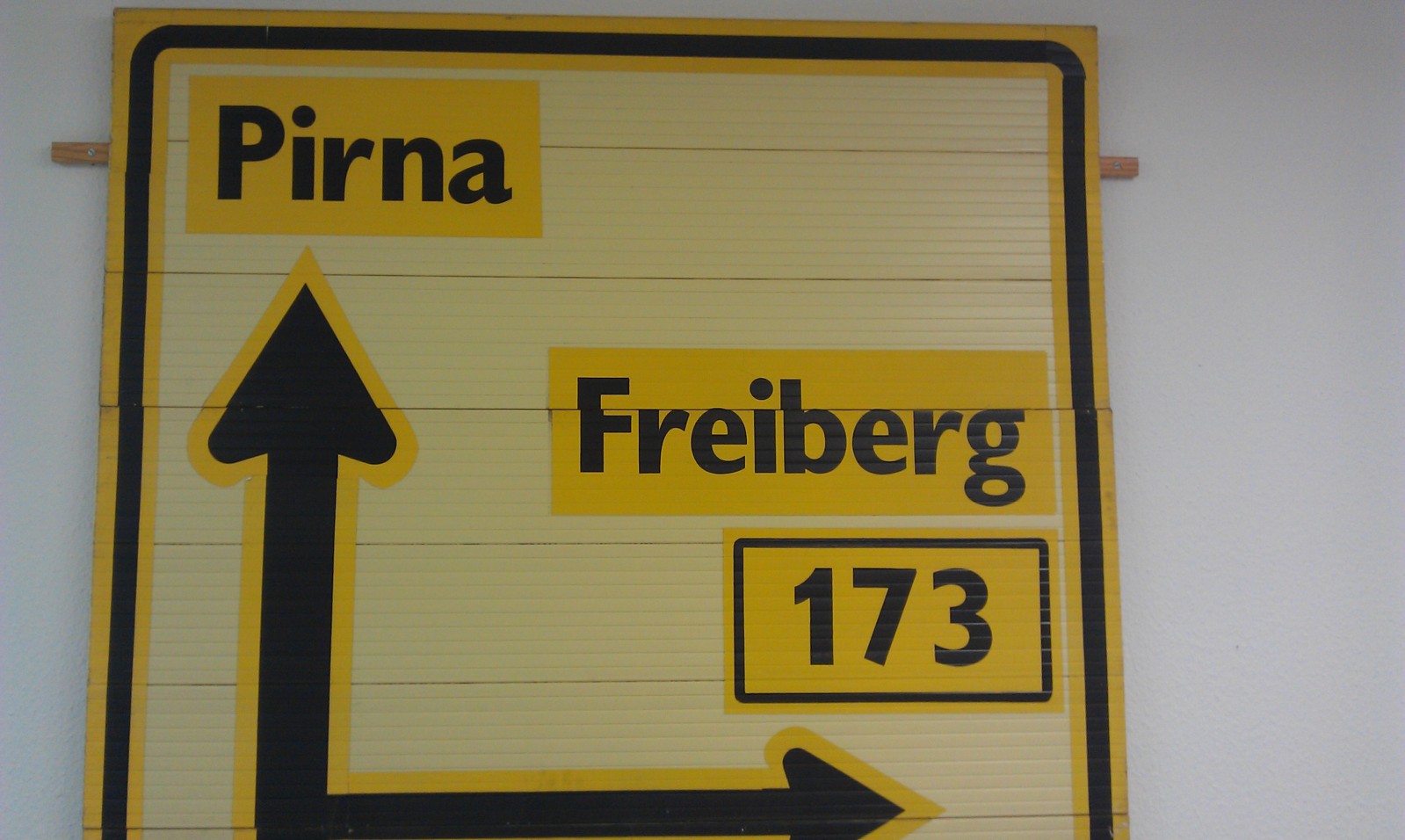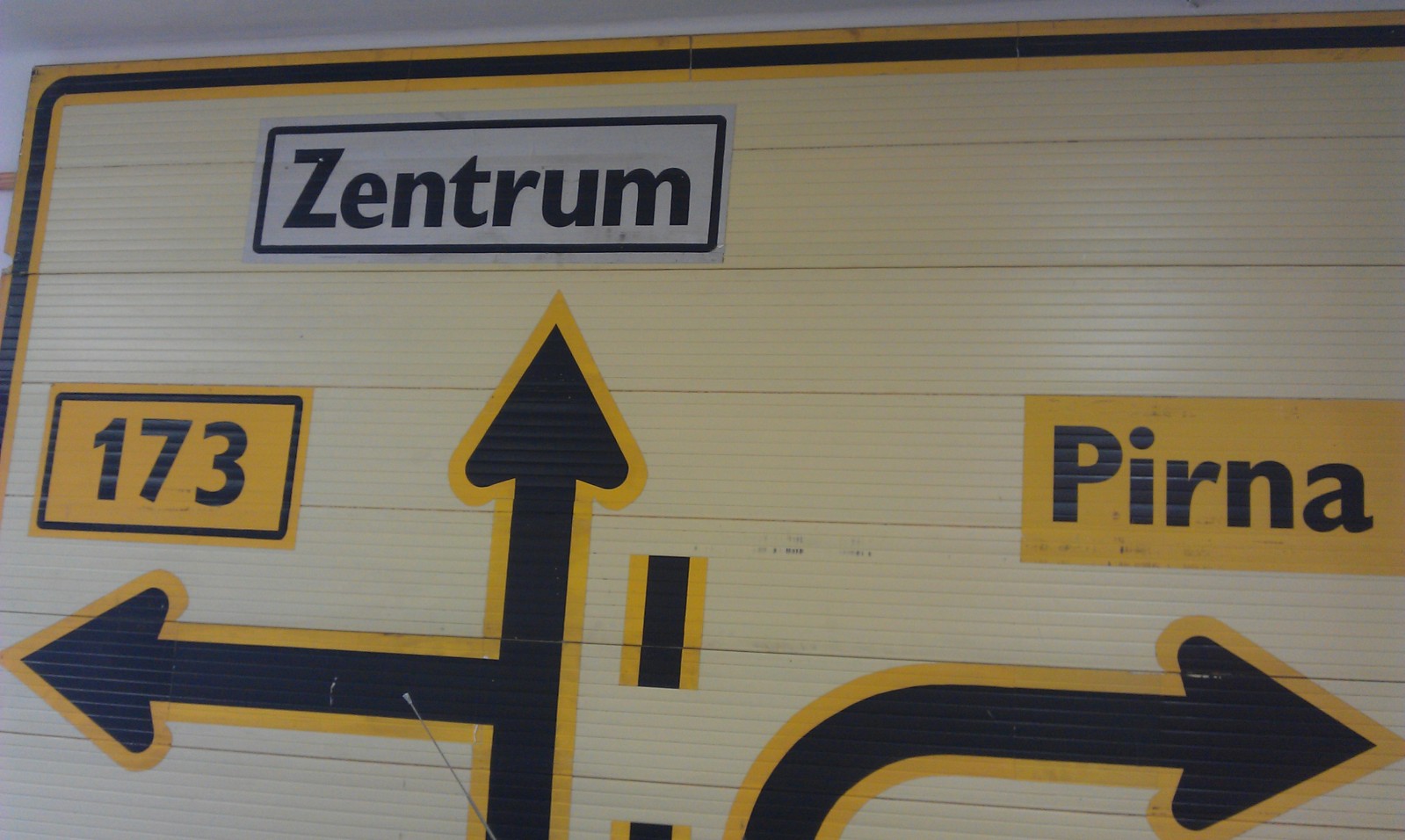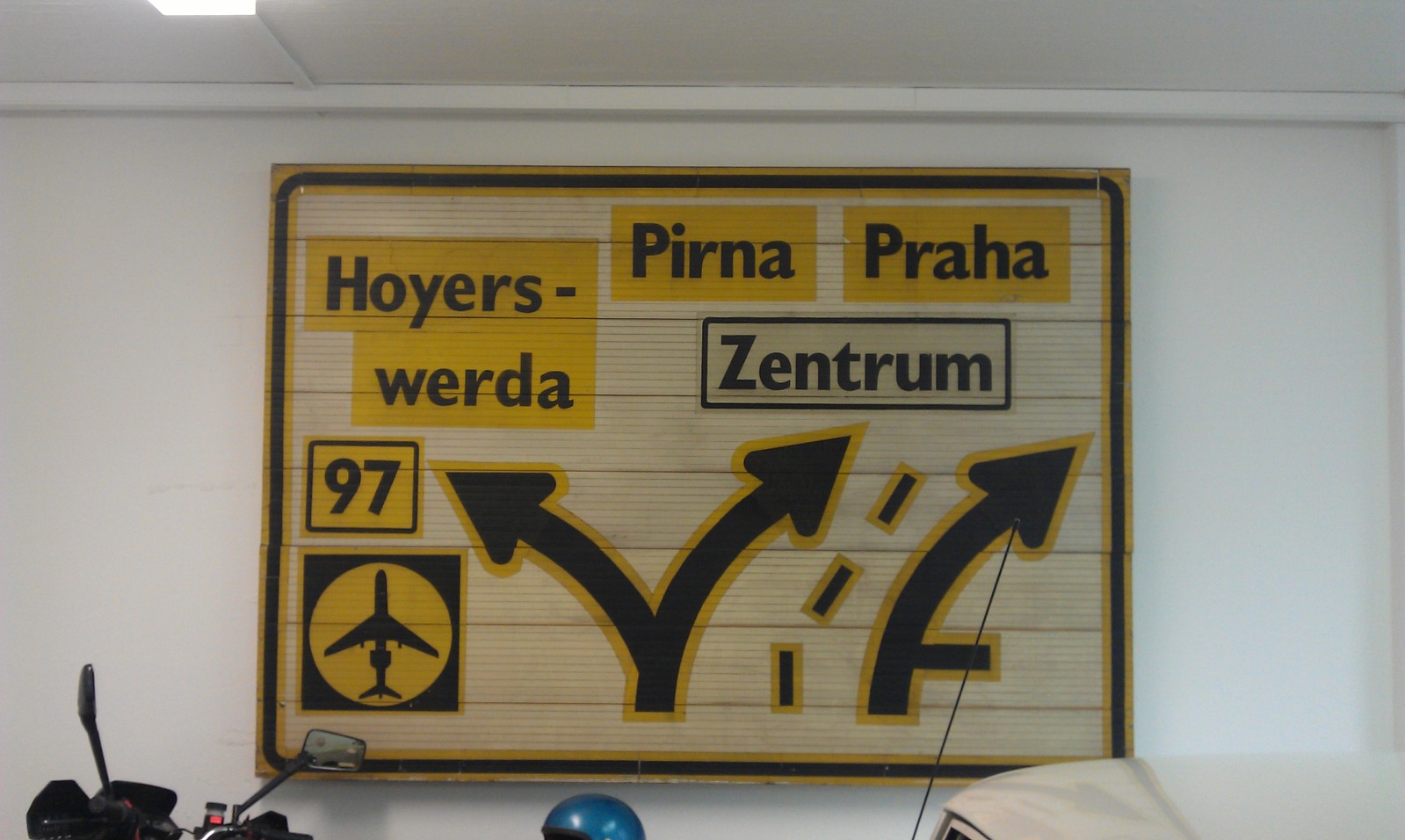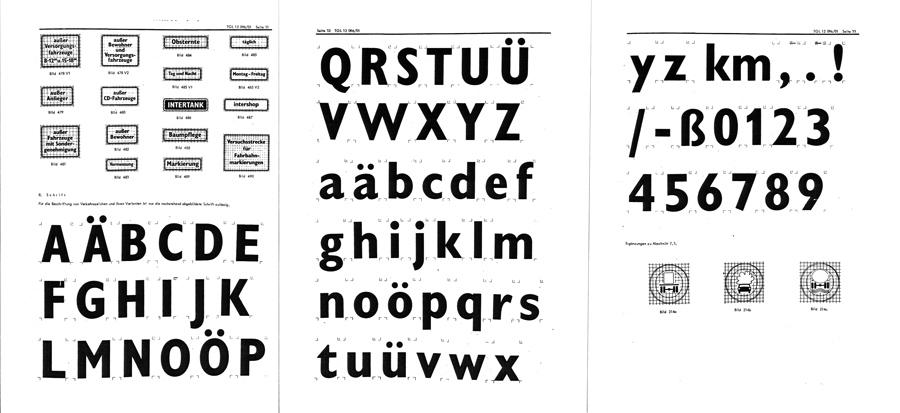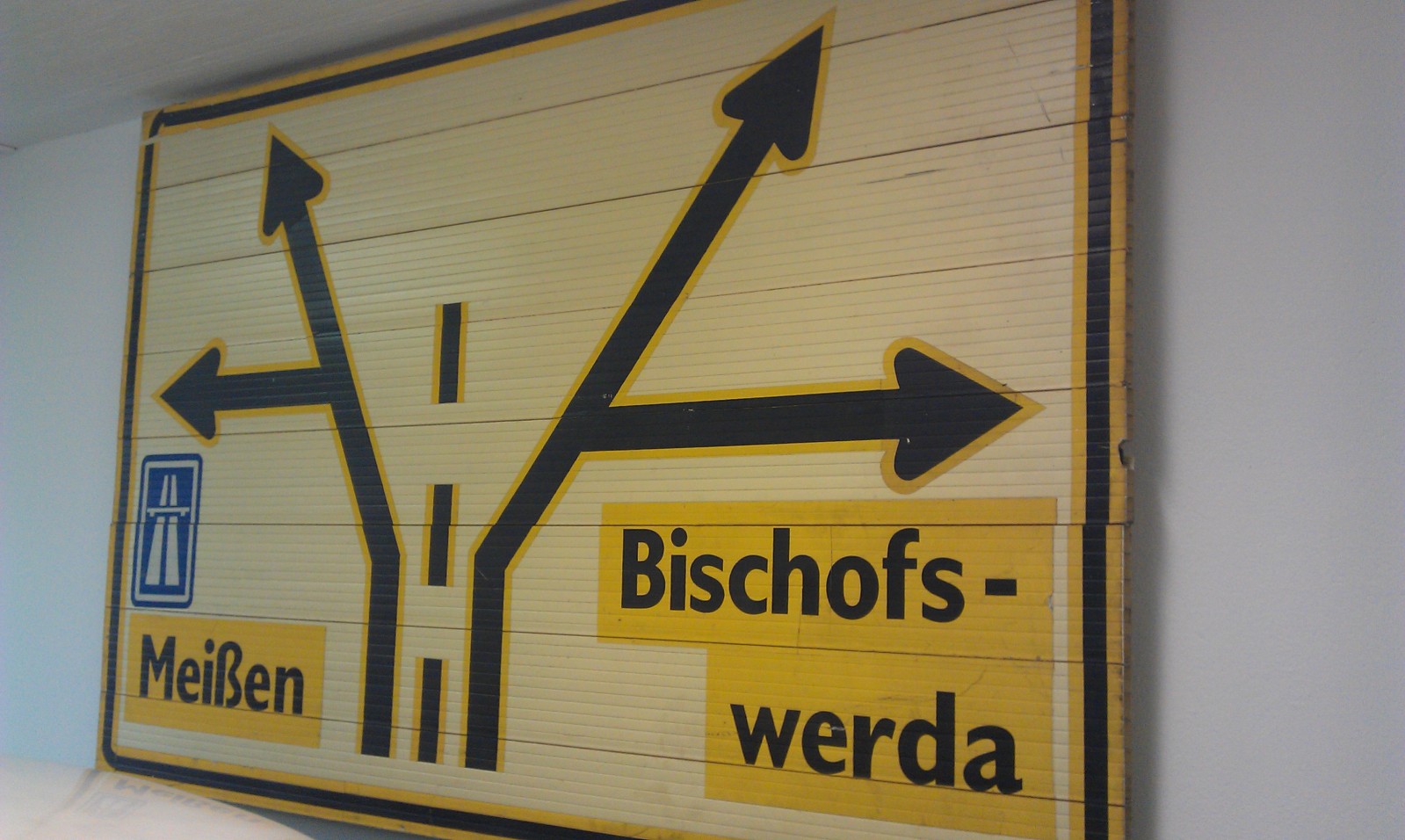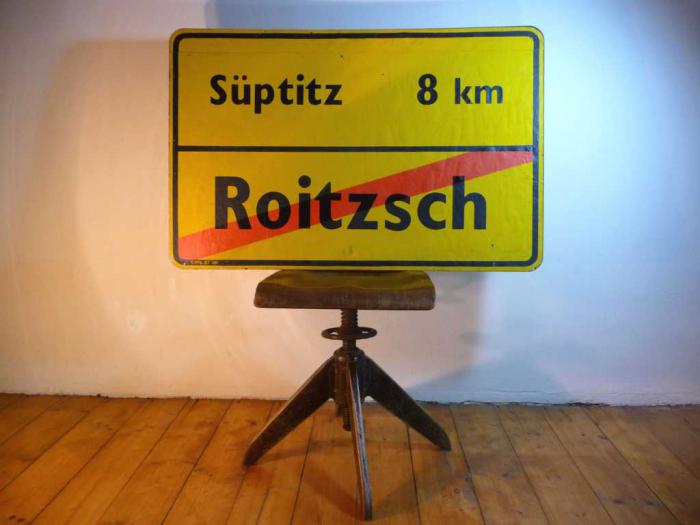
Straßenschilder aus der DDR
Aber die hängen doch nicht an irgendwelchen Wänden, oder? Das sind alte STRAẞEN-Schilder, die gehören an eine Straße und haben den ganz bestimmten Zweck eine Straße zu beschildern ... :mrgreen:
interessant fand ich ja, wie die teile zusammengebaut sind. die bestehen aus plastikschienen – von nah sieht das ziemlich billig aus.
Das Zeug wird bei Frost so spröde, daß man mit einem Stein ein Loch durchwerfen kann.
Ist das eigentlich die normale Typoart-Gill (da habe ich leider keine Schriftmuster) oder gab es für die Verkehrsschilder einen eigenen Schnitt?
Typoart-Gill‽
Na ja, da ich die Gill aus dem Setzkasten kenne, habe ich unterstellt, daß die von Typoart gewesen sei muß. Die kann natürlich auch aus einer Monotype-Setzmaschine gekommen sein, ob das Mono- oder Komplettguß war, weiß ich nicht mehr.